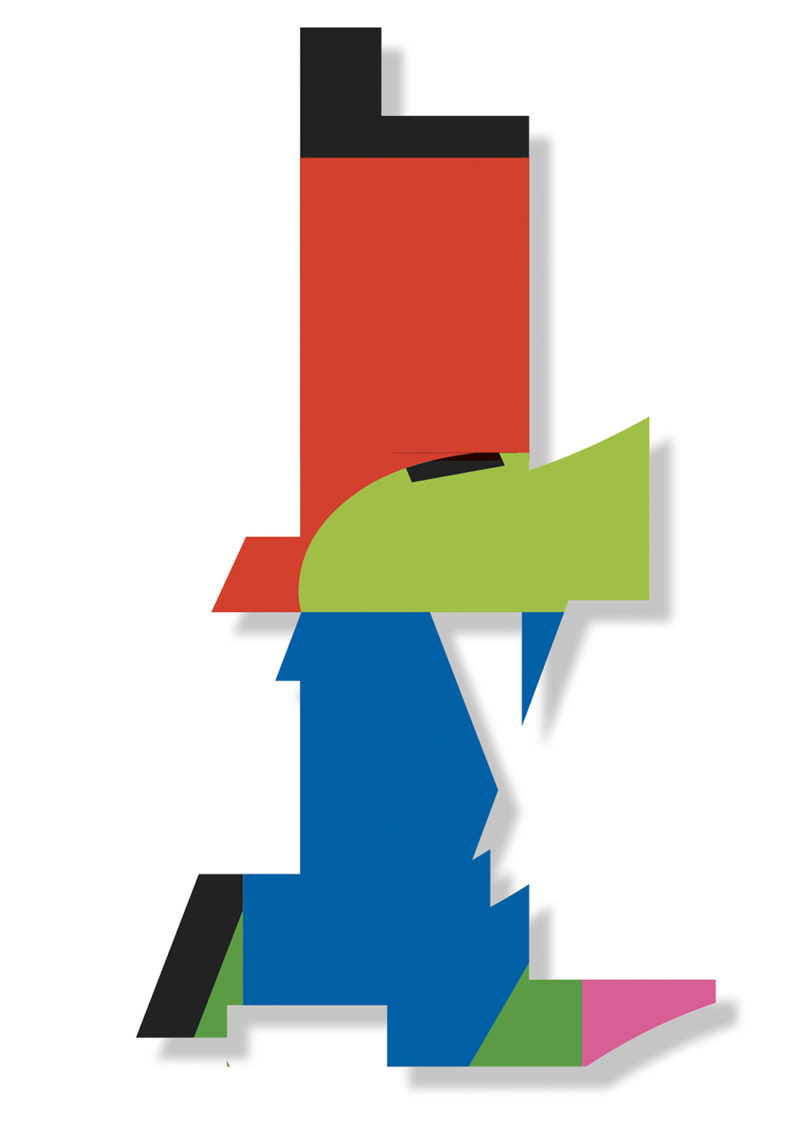
En el trabajo de Pepe Gimeno, las letras no siempre están destinadas a ser leídas. A veces se fragmentan, se acumulan, pierden su función lingüística y comienzan a comportarse como materia visual. Se convierten en estructuras, paisajes, texturas o formas abiertas a nuevas interpretaciones.
Ese desplazamiento constituye el núcleo de Morphosis, la exposición que el Palacio Quintanar de Segovia presenta desde el 24 de julio hasta el 25 de octubre de 2026. La muestra, con Pepe Gimeno como artista y Pedro Medina Reinón como comisario, reúne el resultado de un proceso de investigación iniciado hace más de cinco años con la serie A través de la Posverdad. La dirección del Palacio Quintanar corresponde a Gianni Ferraro.
Más que una recopilación de obras, Morphosis propone hacer visible un proceso. El punto de partida fue una reflexión sobre la manipulación del relato y sobre la manera en que la información puede alterar nuestra percepción de la realidad. A lo largo del tiempo, esa investigación se fue desplazando hacia una cuestión más amplia: cómo construimos sentido, cómo reconocemos las formas y qué mecanismos utilizamos para completar aquello que vemos.
La exposición se sitúa precisamente en ese territorio de tránsito. No presenta la tipografía como un sistema cerrado de signos destinados a transmitir un mensaje verbal, sino como una materia susceptible de ser descompuesta, reorganizada y transformada.
Cuando la letra deja de ser palabra
La tipografía constituye uno de los cuatro ejes que articulan la exposición. En el trabajo de Gimeno, la letra puede desprenderse progresivamente de su función lingüística para adquirir una autonomía visual.
El proceso comienza con un elemento reconocible: una letra, una palabra, un texto o un signo. A partir de ahí, la forma se fragmenta y se somete a diferentes operaciones de transformación. El significado original no desaparece necesariamente, pero deja de ser el único posible.
La letra conserva la memoria de aquello que fue, incluso cuando ya no puede leerse de manera convencional.
Esa tensión entre reconocimiento y extrañamiento resulta esencial en la propuesta. El espectador puede percibir que detrás de una determinada forma existe un lenguaje, pero no siempre consigue reconstruirlo completamente. La imagen se sitúa así en un espacio intermedio entre lo legible y lo visible.
En lugar de entender el texto como una secuencia lineal de signos, Morphosis propone observarlo como un conjunto de formas que pueden ser reorganizadas y generar nuevas relaciones.
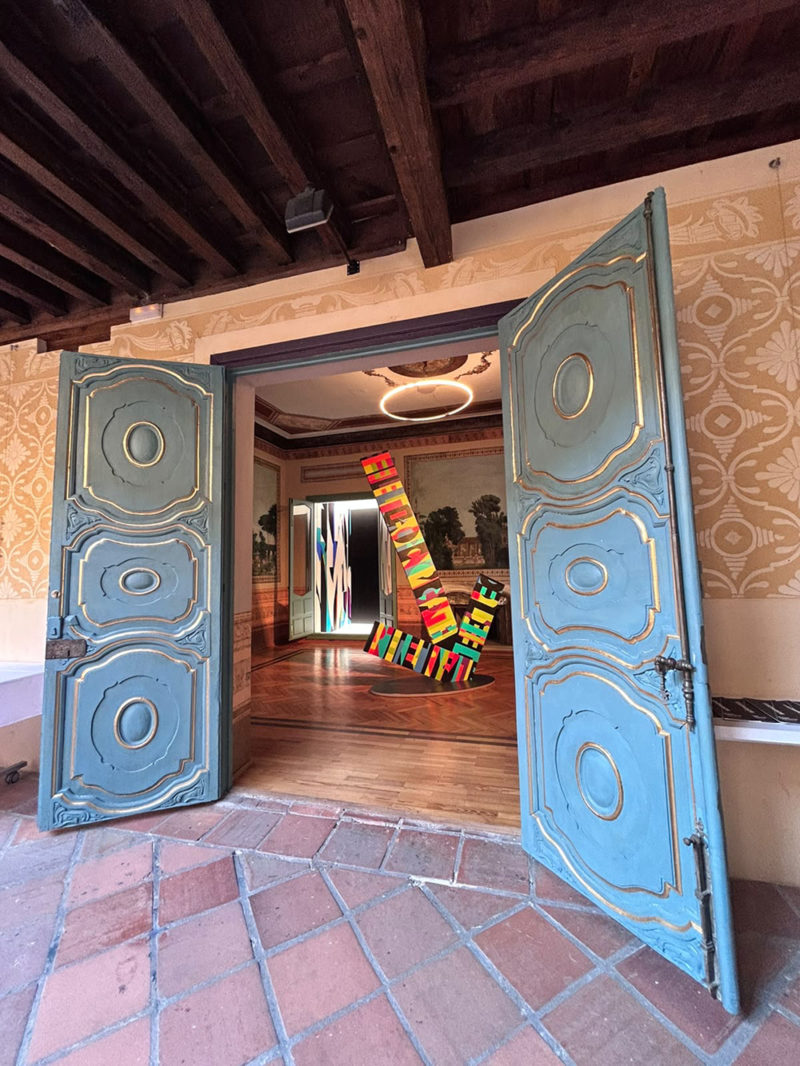
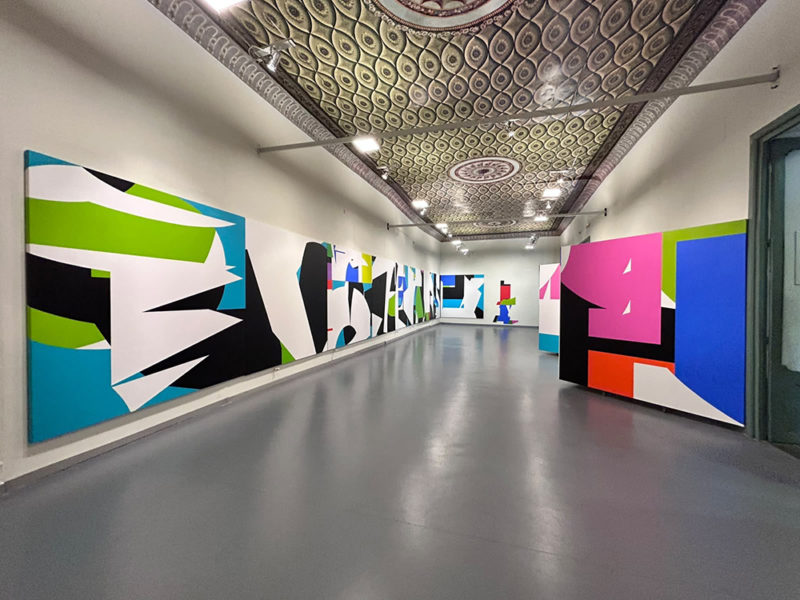
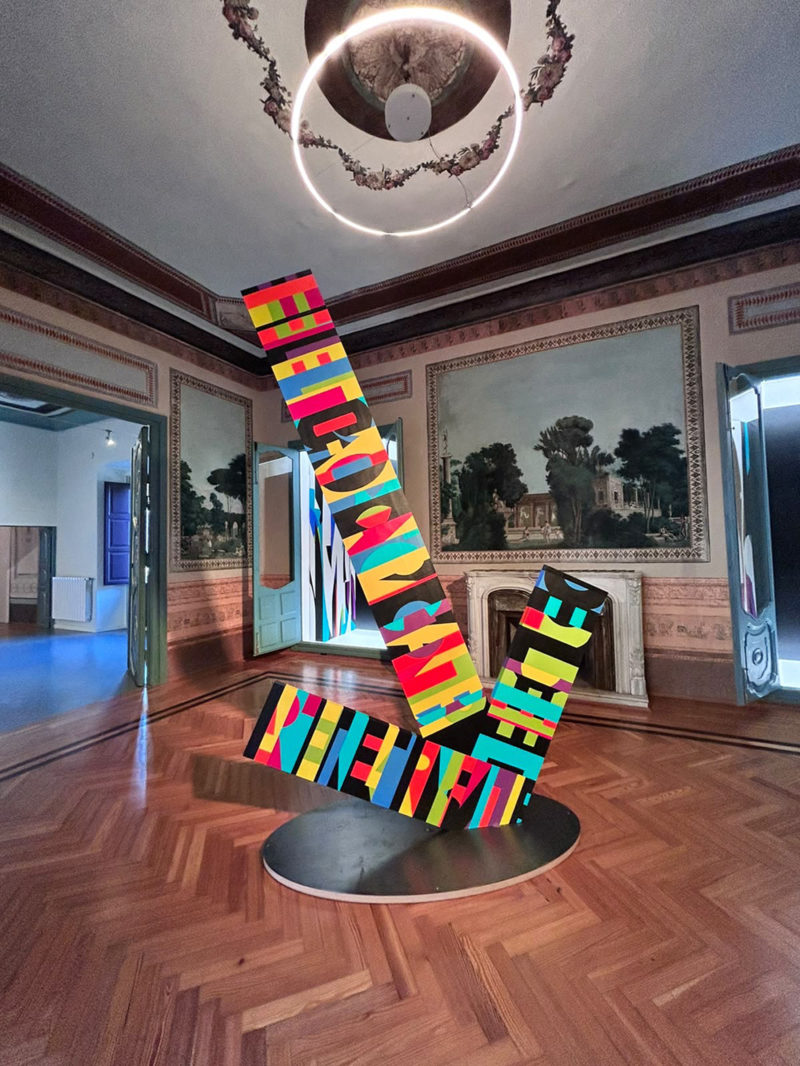
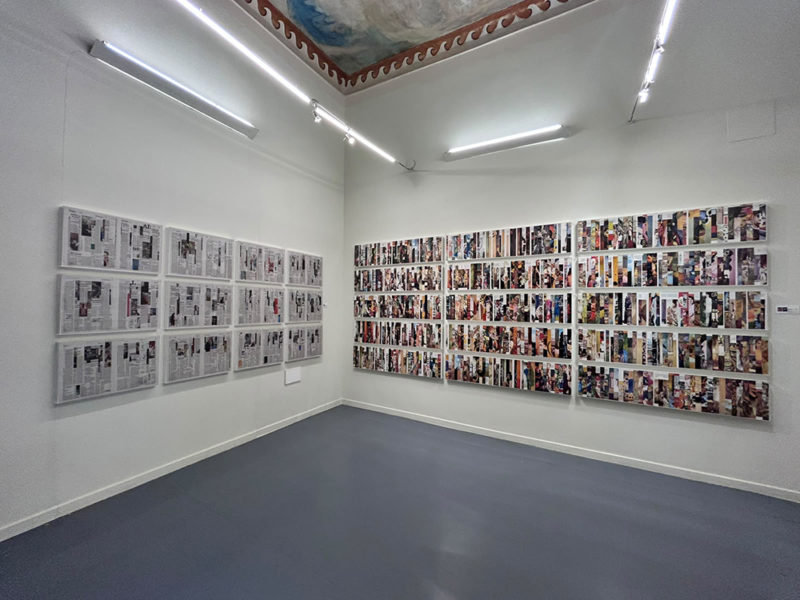
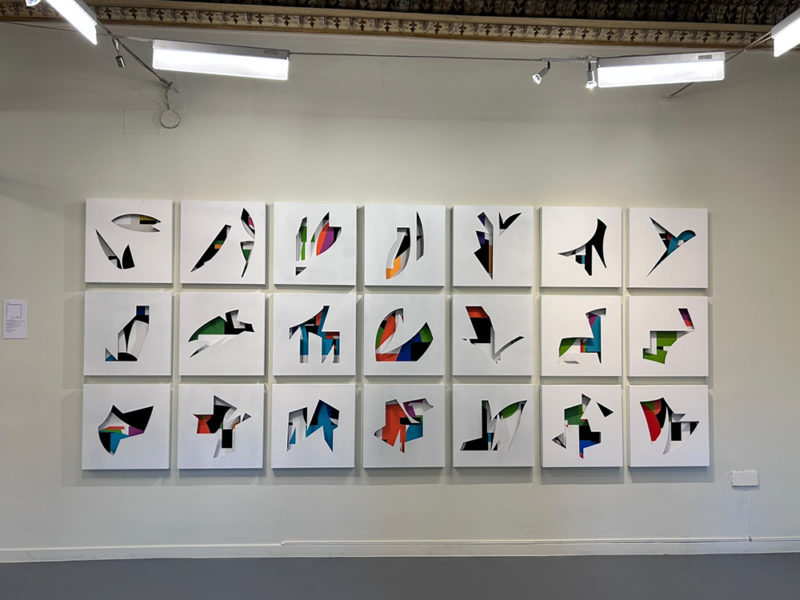
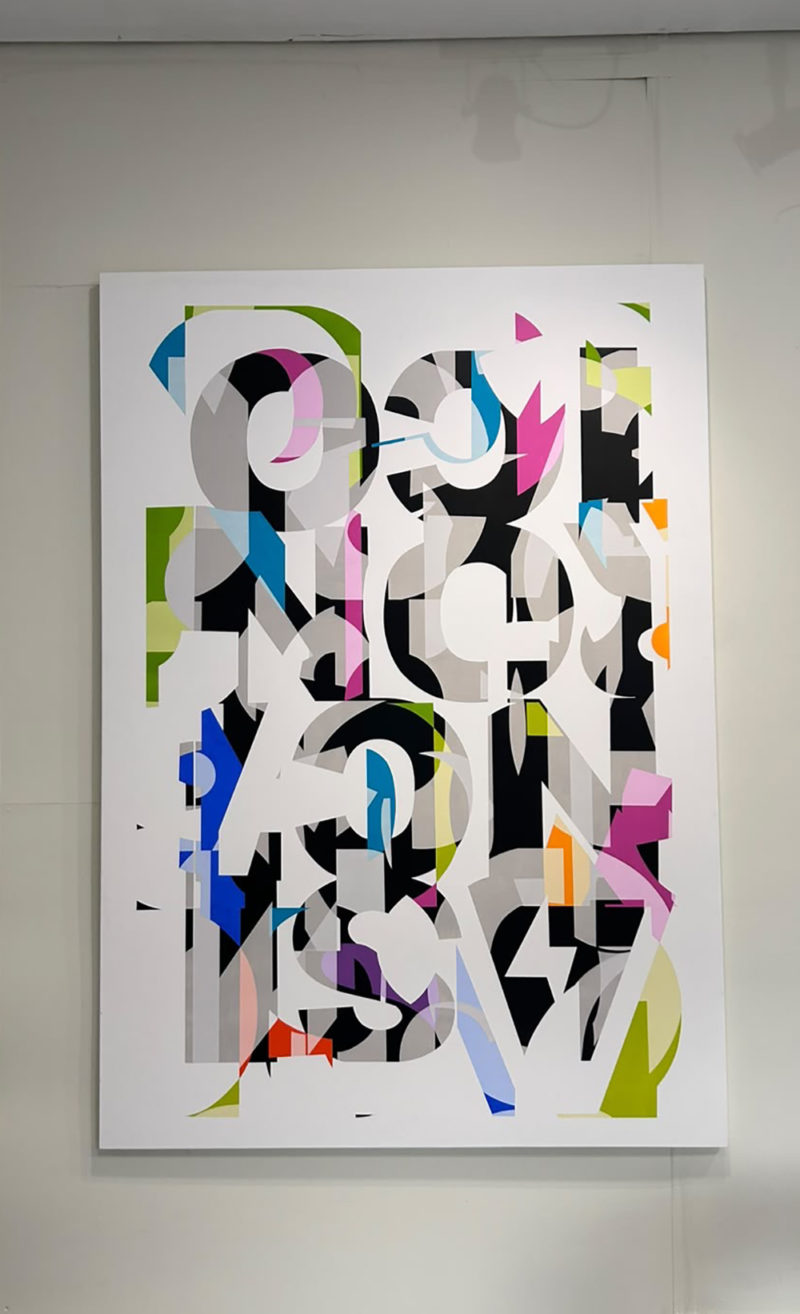
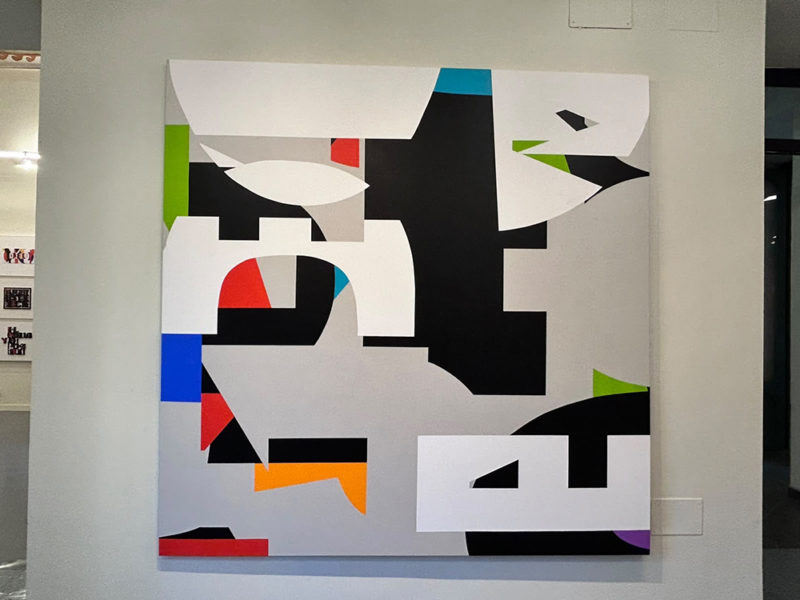
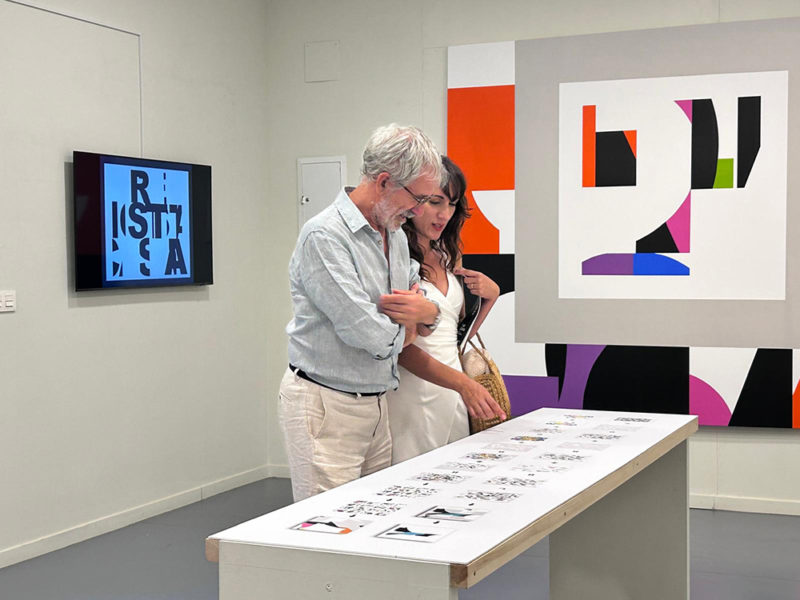
La fragmentación como método
La fragmentación es el segundo gran eje de la exposición. Descomponer una palabra significa alterar su estructura original. Separar sus elementos permite modificar las relaciones entre ellos y abrir nuevas posibilidades de lectura. Cada fragmento mantiene una relación con el conjunto del que procede, pero también puede adquirir una autonomía inesperada.
En este proceso, la fragmentación no equivale a destrucción. Es una estrategia de transformación. El fragmento conserva una memoria. Pero también permite construir algo nuevo.
Esta idea resulta especialmente significativa en una exposición que parte de la manipulación del relato y de la percepción de la realidad. Un relato puede ser descompuesto, reorganizado y presentado de manera diferente sin que necesariamente desaparezcan sus elementos originales. Lo que cambia es la relación entre ellos.
El trabajo de Gimeno traslada esa operación al terreno visual. Las palabras, los signos y las letras se convierten en unidades susceptibles de ser desplazadas y recombinadas. El resultado no es una nueva traducción de un mensaje previo, sino la aparición de una imagen que obliga a reconsiderar la relación entre forma y significado.
El caos como herramienta de creación
El tercer eje de Morphosis es el caos. En este contexto, el caos no aparece como ausencia absoluta de orden, sino como una condición productiva. La acumulación, el azar y la reorganización de los elementos pueden generar combinaciones que no habrían surgido mediante una planificación completamente controlada.
La exposición plantea así una relación entre método y descubrimiento.
El artista establece unas reglas de partida, pero el proceso puede abrir caminos que no estaban previstos inicialmente. La acumulación de fragmentos, su transformación y su posterior reorganización generan nuevas posibilidades formales.
El caos se convierte en una herramienta para encontrar.
Esta manera de trabajar resulta especialmente relevante en una práctica que se apoya en la transformación de materiales previamente existentes. La creación no comienza necesariamente desde una superficie vacía. Puede surgir de la intervención sobre algo que ya contiene información, estructura y memoria.
La obra aparece entonces como resultado de una serie de operaciones: seleccionar, separar, acumular, desplazar, reorganizar y volver a mirar.
Morphosis